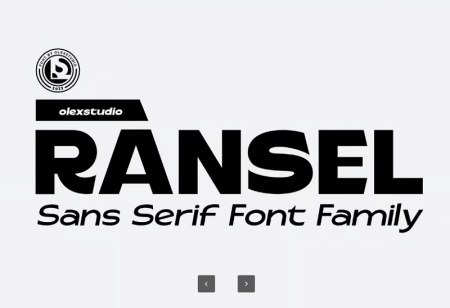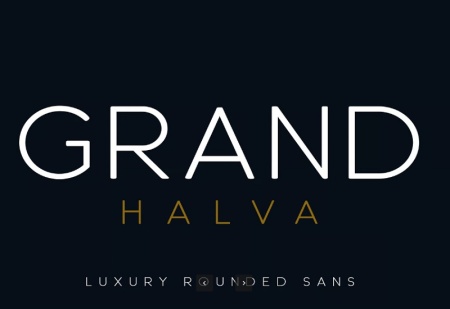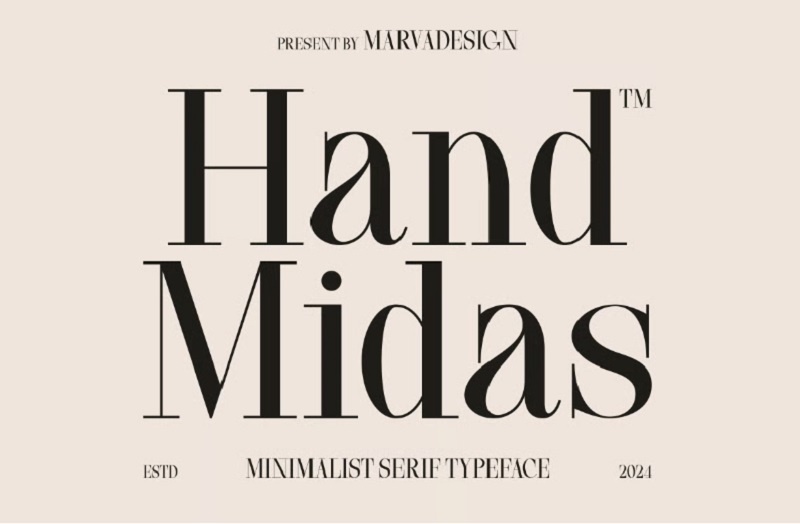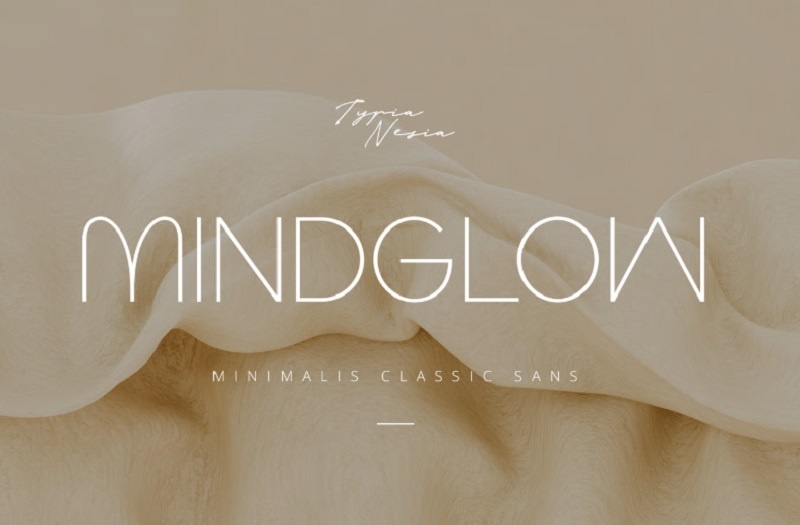
5 فونت انگلیسی برای طراحی کارت ویزیت
دانلود فونت انگلیسی مخصوص کارت ویزیت
فونت انگلیسی برای کارت ویزیت از جی اف ایکس دانلود. این مجموعه شامل بهترین فونت های انگلیسی برای طراحی کارت ویزیت می باشد. فونت های این مجموعه، انتخابی ایده‌آل برای بسیاری از کسب‌وکارها و طراحی کارت ویزیت هستند و برای انواع کسب‌وکارها کاربرد دارد. طراحی کارت ویزیت با این فونت های انگلیسی، کار را برای طراحان راحت‎تر می‌کند.
دانلود فونت انگلیسی برای کارت ویزیت
فونت برای طراحی کارت ویزیت
مجموعه فونت‌های انگلیسی مینیمال برای کارت ویزیت حرفه‌ای
مجموعه فونت‌ های انگلیسی ساده و مینیمال برای طراحی کارت ویزیت
انتخاب فونت‌ های انگلیسی برای کارت ویزیت یکی از مهم‌ ترین مراحل در طراحی حرفه‌ ای و تأثیرگذار است. نوع فونت می‌ تواند برند شما را به‌ صورت مستقیم به مخاطب منتقل کند. فونت‌ های کلاسیک حس اعتماد و رسمیت ایجاد می‌کنند، در حالی‌که فونت‌ های مدرن و مینیمال برای طراحی‌ های خاص و لاکچری کاربرد دارند. اگر در حال طراحی کارت ویزیت برای برندهای بین‌المللی یا کسب‌ و کارهای مدرن هستید، استفاده از فونت‌ های انگلیسی ساده و مینیمال برای طراحی کارت ویزیت، باعث می‌ شود طرح شما حرفه‌ ای‌ تر و چشم‌ نواز تر به نظر برسد. در سایت جی اف ایکس دانلود می‌ توانید انواع فونت‌ های انگلیسی مناسب چاپ کارت ویزیت را با کیفیت بالا و آماده استفاده در فتوشاپ دانلود کنید.
دانلود فونت‌ انگلیسی ساده برای طراحی کارت ویزیت
دانلود فونت انگلیسی برای طراحی کارت ویزیت
✅ نام فونت انگلیسی 1: RANSEL
✅ نام فونت انگلیسی 2: Grand Halva
✅ نام فونت انگلیسی 3: Fancyou
✅ نام فونت انگلیسی 4: Mindglow - Modern Minimalis Classic
✅ نام فونت انگلیسی 5: Hand Midas - A Modern Minimalist Serif Font